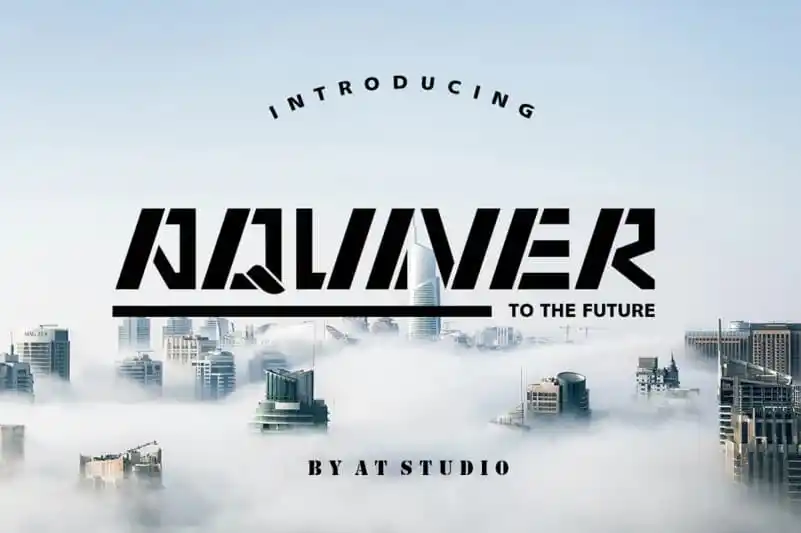
Aquiver Display Font – Download Grátis
A Aquiver Display Font é uma escolha perfeita para aquelas criações que exigem modernidade e futurismo. Com formas linhasas e linhas levemente curvas, essa fonte dá um toque chamativo aos projetos, especialmente para logomarques e aplicativos de jogos. Suas bordas finas e acentos sutis criam uma identidade única que se destaca em qualquer projeto que você esteja desenvolvendo – seja para nome cards, identidades de marca, capas de livros ou até mesmo desenhos personalizados para camisas. Aquiver é versátil o suficiente para atender a um amplo range de necessidades gráficas, tornando-a uma fonte de eleição para designers e criativos do mundo todo.